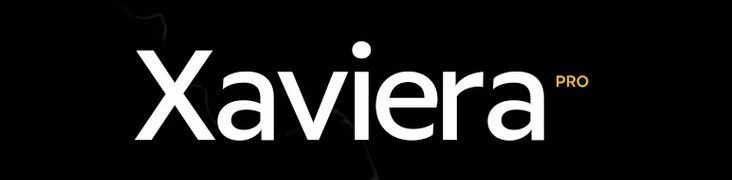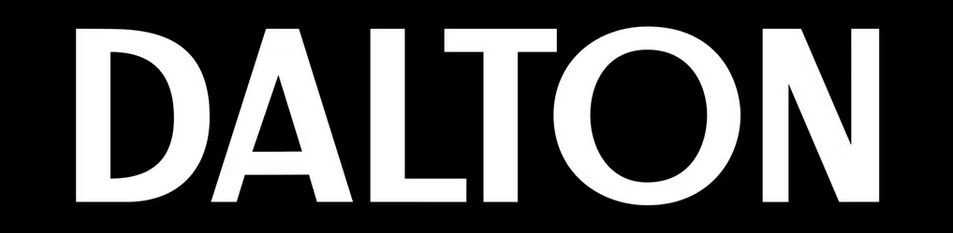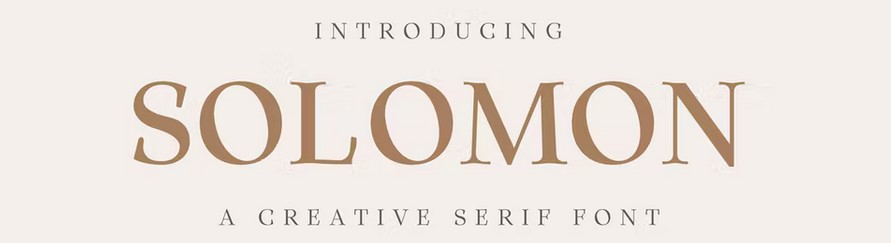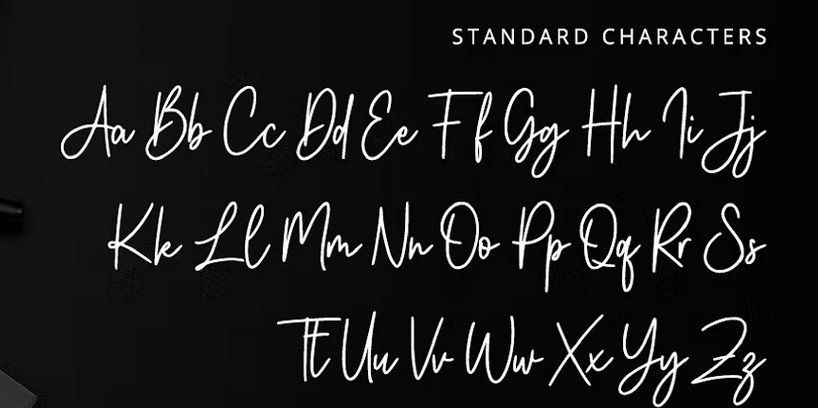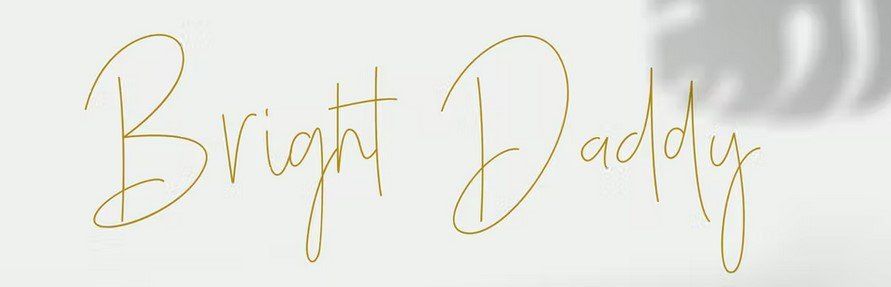
¿Cuál es la mejor fuente para tarjetas de visita?
Hay tantas opciones disponibles para que los empresarios y profesionales creen sus propias tarjetas de presentación que puede ser difícil saber por dónde empezar. ¿Cuál es el mejor lugar para conseguir tarjetas de visita? ¿Qué diseño se adapta mejor a tu marca? ¿Cuál es la fuente perfecta para las tarjetas de visita?
La fuente es uno de los elementos más importantes del diseño de tarjetas de presentación. El tipo de letra hace mucho más que ilustrar el texto. El tipo de fuente afecta la claridad y la legibilidad de una tarjeta de presentación, y la fuente de la tarjeta de presentación establece un tono para la marca, transmitiendo características como profesionalismo, sofisticación y diversión.
Cómo elegir la fuente de su tarjeta de presentación
¿Cómo eliges la fuente de tu tarjeta de presentación? Ya sea que esté personalizando una plantilla o diseñando tarjetas de presentación desde cero, hay miles de fuentes disponibles en los mejores sitios de fuentes, aunque no todas son iguales.
Elegir la fuente incorrecta puede hacer que su marca entregue el mensaje equivocado a su público objetivo. Del mismo modo, muchas fuentes no están diseñadas para la comunicación rápida y clara que se requiere para una fuente de tarjeta de presentación eficaz.
¿No está seguro de cómo elegir buenas fuentes para tarjetas de visita? Los siguientes cuatro consejos deberían ponerlo en el camino correcto.
Elija fuentes de tarjetas de presentación que transmitan el estado de ánimo adecuado.
El diseño de una fuente lleva un mensaje y un tono, y transmite un estado de ánimo que se adjuntará a su marca. Al elegir una fuente para su tarjeta de presentación, asegúrese de seleccionar un tipo de letra que transmita el estado de ánimo que desea representar. ¿Es su pequeña empresa clásica y sofisticada, exclusiva y elegante o divertida y aventurera? Todo esto se puede comunicar en una fuente.
Busca fuentes para tarjetas de presentación que sean originales y de alta legibilidad.
Para diferenciarse de la multitud, desea un diseño de tarjeta de presentación que sea tan único como su marca. Elegir una fuente original ayuda a lograr ese objetivo. Sin embargo, es mejor adoptar un enfoque conservador y no alejarse demasiado de las fuentes tradicionales o correr el riesgo de perder la legibilidad. Si una tarjeta de presentación no es legible, no será efectiva.
Elija una combinación de fuentes que haga que el diseño de su tarjeta de presentación destaque.
Los diseñadores aficionados que crean sus propios patios comerciales pueden querer quedarse con una sola fuente o una sola familia de fuentes para evitar que sus fuentes no coincidan. Sin embargo, si tiene ojo para el diseño, mezclar dos fuentes contrastantes en su tarjeta de presentación puede hacer que el diseño se destaque y capte la atención.
Comprender varias familias de fuentes.
Los diferentes tipos de fuentes transmiten diferentes tonos e incluso pueden transmitir diferentes mensajes, por lo que es importante comprender las categorías de fuentes primarias al seleccionar la fuente perfecta para tarjetas de presentación. ¿Elegirás una fuente sans serif clásica o un tipo de letra serif más sofisticado? Los profesionales creativos pueden incluso optar por agregar elementos de una fuente script para un diseño de tarjeta de presentación único y original.
Fuentes Sans Serif para Tarjetas de Visita
Un tipo de letra sans serif simple es una de las mejores fuentes para tarjetas de presentación debido a las líneas limpias, el estilo clásico y la legibilidad clara. Las sans serif comunes son algunas de las fuentes de tarjetas de presentación más populares porque su simplicidad permite que una fuente sans serif sirva como base para casi cualquier diseño.
1. innumerables profesionales
Como su nombre lo indica, la fuente Myriad Pro de Adobe agrega un toque de profesionalismo a las tarjetas de presentación. La popular fuente sans serif tiene una alta legibilidad y transmite claramente su mensaje en una variedad de tamaños y pesos de fuente.
2. Código fuente
Las fuentes como el código fuente original de Adobe son opciones perfectas para las fuentes de tarjetas de presentación gracias a su claridad, simplicidad y legibilidad. La fuente Source Code es particularmente popular para las tarjetas de presentación en la industria tecnológica, donde las letras se asemejan a los caracteres codificados comunes.
3. Futura
Emocionando el modernismo durante casi un siglo, la fuente Futura, disponible en una variedad de fuentes, incluido Adobe, es un tipo de letra sans serif simple que conserva una alta legibilidad en el diseño de una tarjeta de presentación. Los diseñadores disfrutan del generoso espacio entre líneas en Futura, y sus diversos pesos disponibles le permiten complementar una multitud de diseños de tarjetas de presentación.
4. Relación
Otra gran fuente para tarjetas de presentación, la opción de fuente Ratio sans serif presenta líneas suaves y elegantes para una apariencia clara y profesional. La fuente Ratio, disponible en Adobe Fonts y otras fuentes populares, brinda una sensación moderna para las tarjetas de presentación en los sectores contemporáneos.
5. arenas movedizas
La fuente Quicksand es otro tipo de letra sans serif efectivo adecuado para tarjetas de presentación. Disponible en una variedad de fuentes en línea, incluidas Adobe Fonts, Quicksand presenta amplios espacios y caracteres extravagantes que brindan una apariencia única a cualquier diseño de tarjeta de presentación.
6. Gibson
Debido a que es tan fácil de leer, la fuente Gibson sigue siendo una de las fuentes sans serif más populares para tarjetas de presentación. Disponible en Adobe y otros recursos, Gibson se considera una fuente humanista que brilla en casi cualquier diseño.
7. Javiera
¿Estás buscando la fuente perfecta para tarjetas de presentación? ¿Por qué no seleccionar un tipo de letra creado solo para ese propósito? Xaviera es una selección profesional de fuentes sans serif que diseña exclusivamente para tarjetas de presentación, así como para publicidad gráfica e impresión en línea. Los caracteres sencillos de la fuente Xaviera, disponibles en Envato Elements y otras fuentes populares, combinan bien con anclas con guión o novedosas.
8. Dalton
Dalton es una fuente comercial moderna perfecta para hacer una declaración en una tarjeta de presentación. La fuente sans serif Dalton emana profesionalismo y envía un mensaje claro. El tipo de letra está disponible en Envato Elements.
Fuentes Serif para Tarjetas de Visita
Las fuentes Serif también son opciones efectivas como tipos de letra para tarjetas de presentación gracias a su apariencia clásica y profesional. En tipografía, una serifa se refiere a una pequeña línea o trazo que se adjunta al final de un trazo más grande en un carácter escrito o mecanografiado. Estos pequeños detalles pueden alterar drásticamente la apariencia de una fuente y, cuando se usan de manera efectiva, pueden darle vida a un diseño que de otro modo sería simple y aburrido.
9. Trajano
Trajano | fuentes de adobe
Inspirada en las letras romanas clásicas, la fuente Trajan de Adobe agrega un toque de estilo atemporal al diseño de una tarjeta de presentación. La elegancia clásica de la fuente serif transmite profesionalismo sin dejar de destacar entre la multitud.
10. Esbirro
Con un estilo similar al universalmente popular Times New Roman, la fuente Minion serif fue diseñada para el cuerpo del texto hace más de 30 años. La fuente Minion, un tipo de letra original de Adobe Fonts, le da a las tarjetas de presentación un aspecto clásico pero profesional.
11. Canaya
¿Quieres darle un aire de elegancia a tu tarjeta de visita? La fuente Qanaya es un tipo de letra serif que está disponible en Envato Elements y otras fuentes en una variedad de pesos y tamaños de fuente.
12. Salomón
Otra opción popular de fuente serif para tarjetas de presentación disponible en Envato Elements, la fuente Solomon presenta un diseño creativo que agregará estilo a una tarjeta de presentación normal y conservará su elegancia y legibilidad.
13. Baskerville PT
Otra hermosa opción de fuente para tarjetas de presentación, Baskerville PT es un elegante tipo de letra serif que promete brindar un auro de profesionalismo. La fuente versátil está disponible en una variedad de tamaños y pesos, manteniendo su apariencia clásica en múltiples formatos.
Fuentes Script para Tarjetas de Visita
Si bien las fuentes de escritura, tipos de letra que se asemejan a la escritura cursiva, no se recomiendan como fuente principal para tarjetas de presentación, pueden agregar un toque creativo cuando se usan con moderación. Considere captar la atención con su tarjeta de presentación eligiendo una fuente de script para un título o nombre de empresa. Sin embargo, evite los tipos de letra script para los detalles debido a la legibilidad reducida.
14. ramo
Deportivo y emocionante, el tipo de letra Bouquet es una fuente de escritura caracterizada por letras cursivas gruesas. La fuente Bouquet, disponible en Envato Elements y otras fuentes, hará una fuerte declaración con un mensaje legible cuando se use en una capacidad limitada en una tarjeta de presentación.
15. Firma cursiva
¿Busca una fuente de escritura simple pero elegante para resaltar su tarjeta de presentación? La fuente Signature Cursive, disponible en Envato Elements, consta de caracteres elegantes dibujados con trazos elegantes.
16. Papá brillante
El tipo de letra Bright Daddy, disponible en línea de fuentes como Envato Elements, presenta un diseño natural y fluido que podría servir como una forma efectiva de resaltar los temas principales en un diseño de tarjeta de presentación que de otro modo sería olvidable.
¿Cuál es la mejor fuente para tarjetas de visita?
Con tantas opciones disponibles, puede ser difícil determinar cuál es la mejor fuente para las tarjetas de presentación. La mejor fuente para tarjetas de presentación es aquella que es clara y legible, pero que conserva la profesionalidad y la originalidad. Por lo tanto, la mejor fuente para tarjetas de presentación es claramente Baskeville PT. La fuente es versátil e incluye una variedad de opciones al tiempo que ofrece un toque de elegancia y profesionalismo.
¿Cuál es la mejor fuente sans serif para tarjetas de visita?
Por una variedad de razones, algunas personas prefieren las fuentes sans serif para sus tarjetas de presentación. Las fuentes sans serrif son clásicas y brindan una legibilidad clara en múltiples tamaños y formatos. La mejor fuente sans serif para tarjetas de presentación es Xaviera. Los caracteres nítidos y claros prometen destacar y captar la atención de los destinatarios.
¿Cuál es el tamaño estándar para las fuentes de las tarjetas de presentación?
¿Cuáles son los mejores tamaños de fuente para las tarjetas de presentación? El tamaño estándar de las fuentes de las tarjetas de presentación es de 10 pt. Tenga en cuenta que cuando se usa 10 pt para el tamaño de fuente principal, los detalles como la información de contacto se adaptarán mejor a un tamaño de fuente más pequeño de 9 u 8 pt. Recuerde, no imprima ninguna información en su tarjeta de presentación en un tamaño de letra inferior a 8 pt.